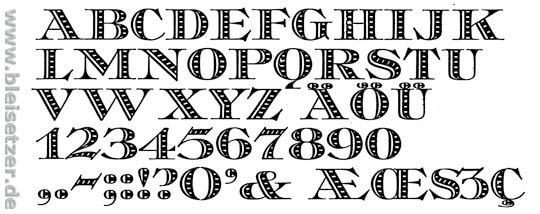
Es ist ein Zeichen, daß es im original Bleisatz-Zeichensatz der Schriften nicht gab. Ah, ich sehe gerade: Ja, es ist ein @ sign.
Das @ Zeichen:
Die Schrift war übrigens gerade großes Thema, als ich vor.. ich weiß nicht mehr wievielen Monaten hier das Forum zum ersten mal besuchte. Bzw. die Schrift war Teil einer anderen Debatte eines anderen typographischen Themas.
Im Bleisatz gibt es heute auch @ Zeichen.
Aber leider nur in zwei Versionen:
Als Antiqua-Version und als kursive Antiqua-Version.
Warum das so ist, weiß ich nicht.
Toll finde ich bei den digitalisierten Schriften, daß die @ Zeichen
dem Gemeinen a der jeweiligen Schrift zu entsprechen scheinen.
Die Schrift hat etwas sehr sehr seltenes.
Und genau dieses "Seltene" war vor rd. einem Jahr
großes Thema in einem Fach-Magazin.. sagt man so?
Und wurde auch hier tagelang durchdiskutiert.
Das hier ist übrigens auch eine schöne Schrift,
wenn auch nicht die gesuchte:
Die Tauperle von Albert Auspurg von 1922:
Die Versal-ß Diskussion und diese Ausgabe der Signum über das Thema.
Deshalb die Brücke mit der Tauperle. Beide, Ehmcke und Tauperle, haben ja das Versal-ß, wenn auch ein völlig unterschiedliches. Ich wollt's halt mal etwas komplizierter machen als bei meinem letzten Versuch..
Das ist gelungen. Gigt es eigentlich von der Ehmke inzwischen eine digitale Variante? Hier jedenfalls die neue Aufgabe:
NEIN, ich weiss nicht was das dort oben ist ... vielleicht ein script 'h'?
Nein, keines der genannten Zeichen. Nicht die Bello, auch keine andere Script. Der Hintergrund ist weiß. Ich lass Euch noch ein Stündchen raten, wenn bis dahin keiner das Zeichen hat gibt es einen größeren Ausschnitt. Gute besserung, Robertmichael.
Nein, kein b. Ich gebs ja zu, der Ausschnitt ist etwas irreführend.
Na gut, etwas mehr. Der Buchstabe sollte jetzt klar sein, oder?